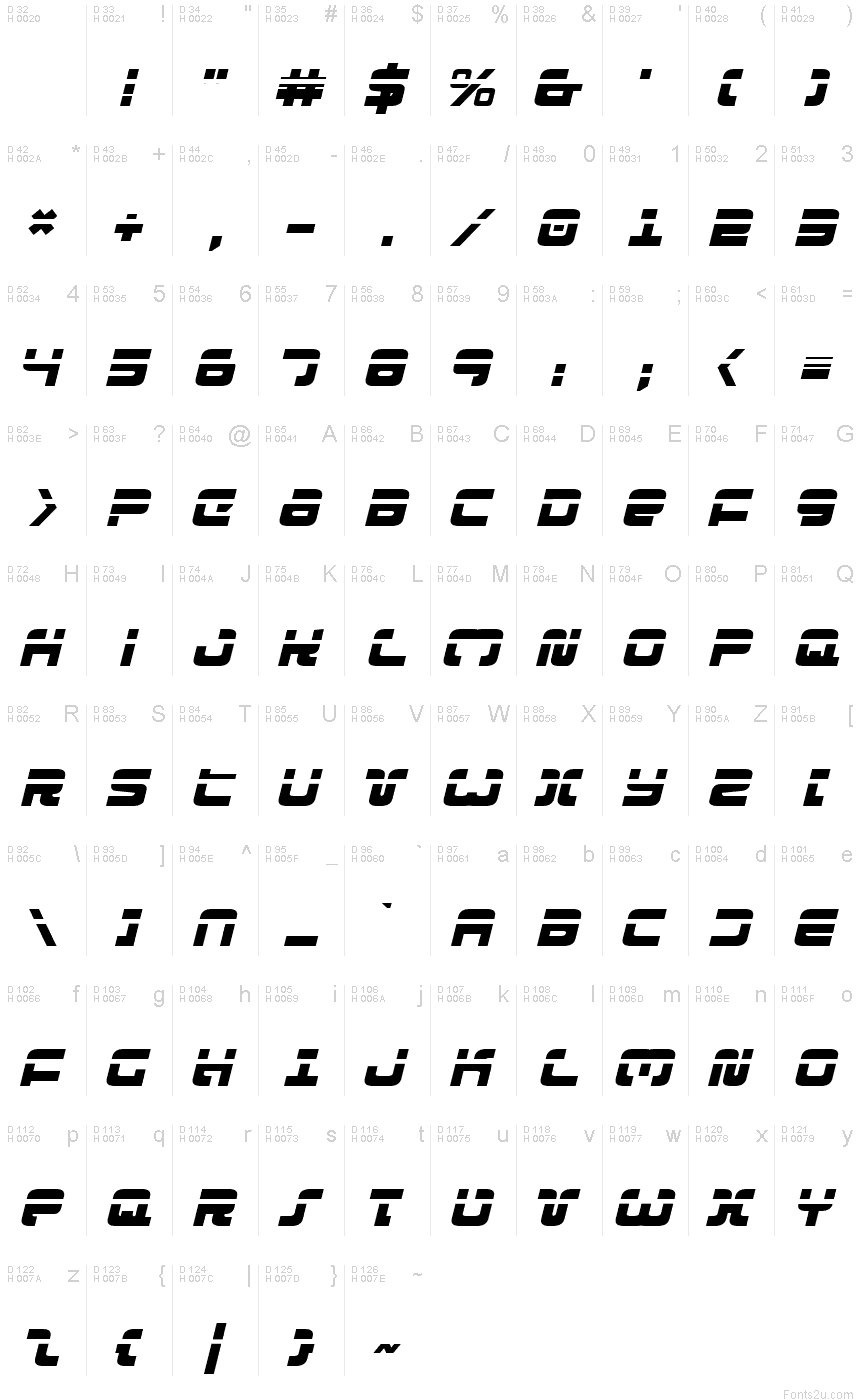
Exedore Laser Italic, eine kostenlose, futuristische Stencil-Display-Schrift von Iconian Fonts, fängt die Geschwindigkeit von Sci-Fi-Fahrzeuggrafiken ein. Ihre stark geneigten Buchstaben verbinden breite, solide Formen mit sauberen horizontalen Einschnitten und erzeugen so einen tiefen, konstruierten Rhythmus, der wie für die Bewegung gemacht wirkt.
Diese Vorwärtsneigung sorgt für Dringlichkeit in Racing-Identitäten und Esports-Branding, während die segmentierte Konstruktion Spieletiteln und Technikverpackungen einen markanten, mechanischen Schliff verleiht. Verwenden Sie diese kostenlose Schrift für Event-Poster oder Streaming-Grafiken, wenn die Komposition Beschriftungen verlangt, die sich perfekt in eckige Grafiken einfügen und eine überzeugende Arcade-Zukunftsstimmung vermitteln.